毛笔字体设计现在已经成为了一种潮流。随着社会的不断发展,人们的品位和审美也有了新的提高。在现代社会中,楷体、草书等经典字体已经不再符合现代人的审美观,因为现代人接触了很多新型的字体,所以审美自然也会有所改变。经典字体有经典字体的美感,但现代字体也有属于现代字体的与众不同,既然生活在现代,那么不如让字体也更符合现代人的审美。下面,义启字库将为大家介绍毛笔字体设计的相关内容。
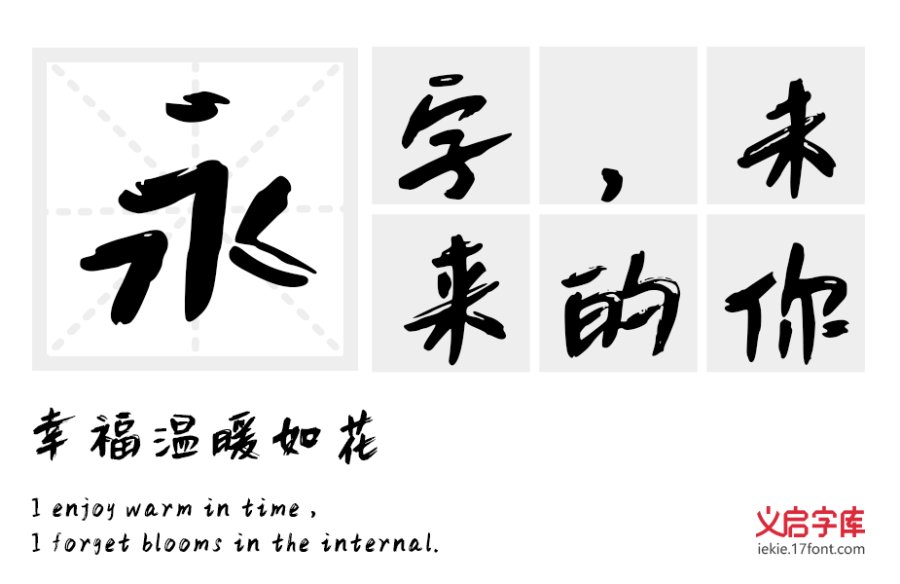
毛笔字体设计是连毛笔字体设计、断毛笔字体设计、单毛笔字体设计的一个统称。毛笔字体设计可以让经典的字体呈现出现代的美感,所以它的意义和价值还是比较大的。对于现代人来说,不仅仅要让科技得到重生,更要让传统书法字体得到传承。书法字体代表着人类的一种审美,也代表着一种技术,就算是到了人工智能时代,毛笔手写体也永久不会逝去。
毛笔字体设计不仅仅可以在结构上改变字体,而且还可以改变字体的整体美感,所以毛笔字体设计是比较常用的字体设计方法。很多年轻人在进行字体设计时,都会用到毛笔字体设计,因为毛笔字体设计可以让经典字体焕然新生。
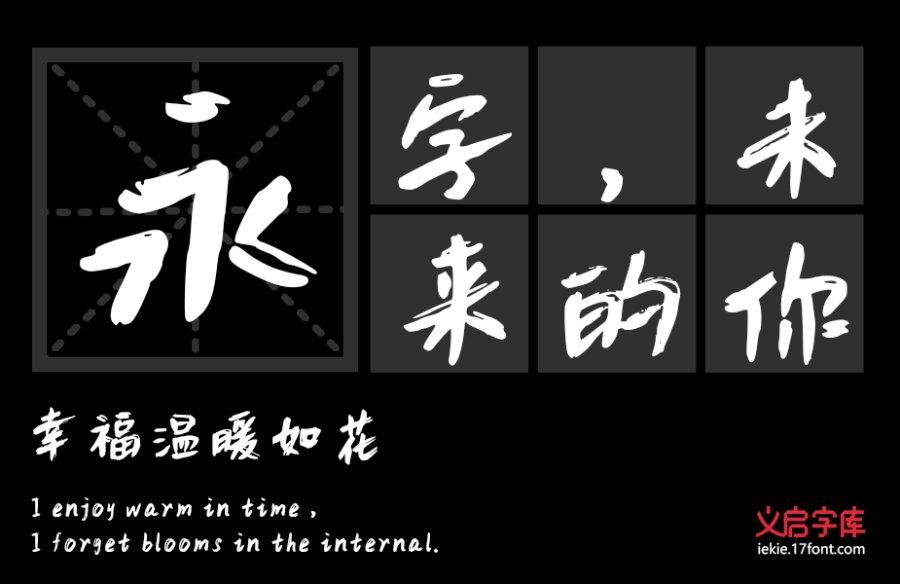
毛笔字体设计的优点还是比较多的,其一它的适用范围比较广,可以适用于多种不同的字体设计。其二,毛笔字体设计是可以改变字体的形态与结构,这对于字体设计来说是非常重要的。
以上就是义启字库为大家介绍的毛笔字体设计的相关内容,毛笔字体设计真的是一种比较实用的字体设计方法,喜欢的可以了解一下。